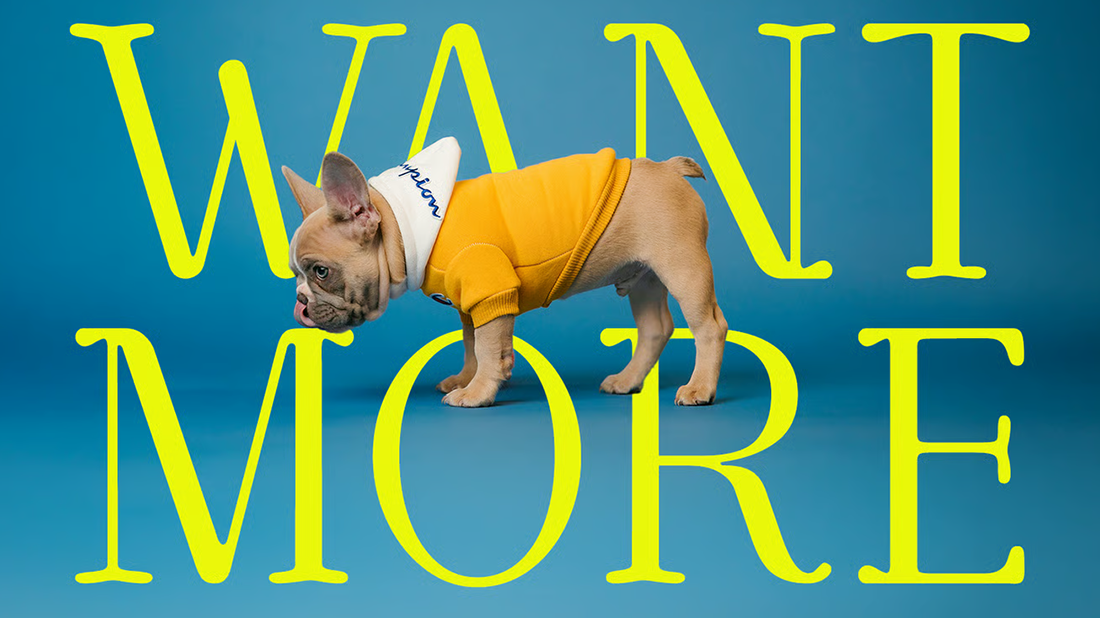
معرفی فونت انگلیسی cortexo typeface
فونت انگلیسی cortexo typeface, یا همان Cortexo Typeface، یک قلم کلاسیک و مدرن از نوع thin serif است که توسط Foxtype طراحی شده. این فونت با دقتی استادانه و خطوطی شفاف طراحی شده تا پروژههای هنری، لوکس و باکیفیت شما را ارتقا دهد.
ویژگیهای برجسته فونت انگلیسی cortexo typeface
طراحی نازک و ظریف
Cortexo فرمهای باریک و سریفهایی نرم دارد که ظاهر آن را همخوان با طراحیهای لوکس و مینیمال میکند.
عالی برای طراحی جلد مجله، تیتر پوسترهای شکیل، برندینگ لوکس، لوگوها و پروژههای ادیتوریال.پشتیبانی زبانی گسترده
با پوشش بیش از ۲۱۶ زبان جهانی، Cortexo برای پروژههای بینالمللی بسیار مؤثر و منعطف است.
کاربردهای پیشنهادی با آیکون
جلد مجله و تیترهای کلاسیک – ظرافت بصری با بیان لوکس
برندینگ لوکس و حرفهای – ایجاد هویتی باوقار و متمایز
دعوتنامههای خاص یا کارت رویداد – انتقال حس خاص و فاخر
طراحی وب مدرن – استفاده در بخشهای تأکیدی مثل هدرها و بنرها
جمعبندی
فونت Cortexo Typeface با ترکیبی از خطوط ظریف، سریف مدرن و پشتیبانی زبانی گسترده، سهمی استثنایی در ساخت پروژههای باکیفیت و شکیل دارد. اگر دنبال القای حس لوکس، حرفهای و خوانا در طراحیهات هستی، Cortexo گزینهای ممتاز خواهد بود.